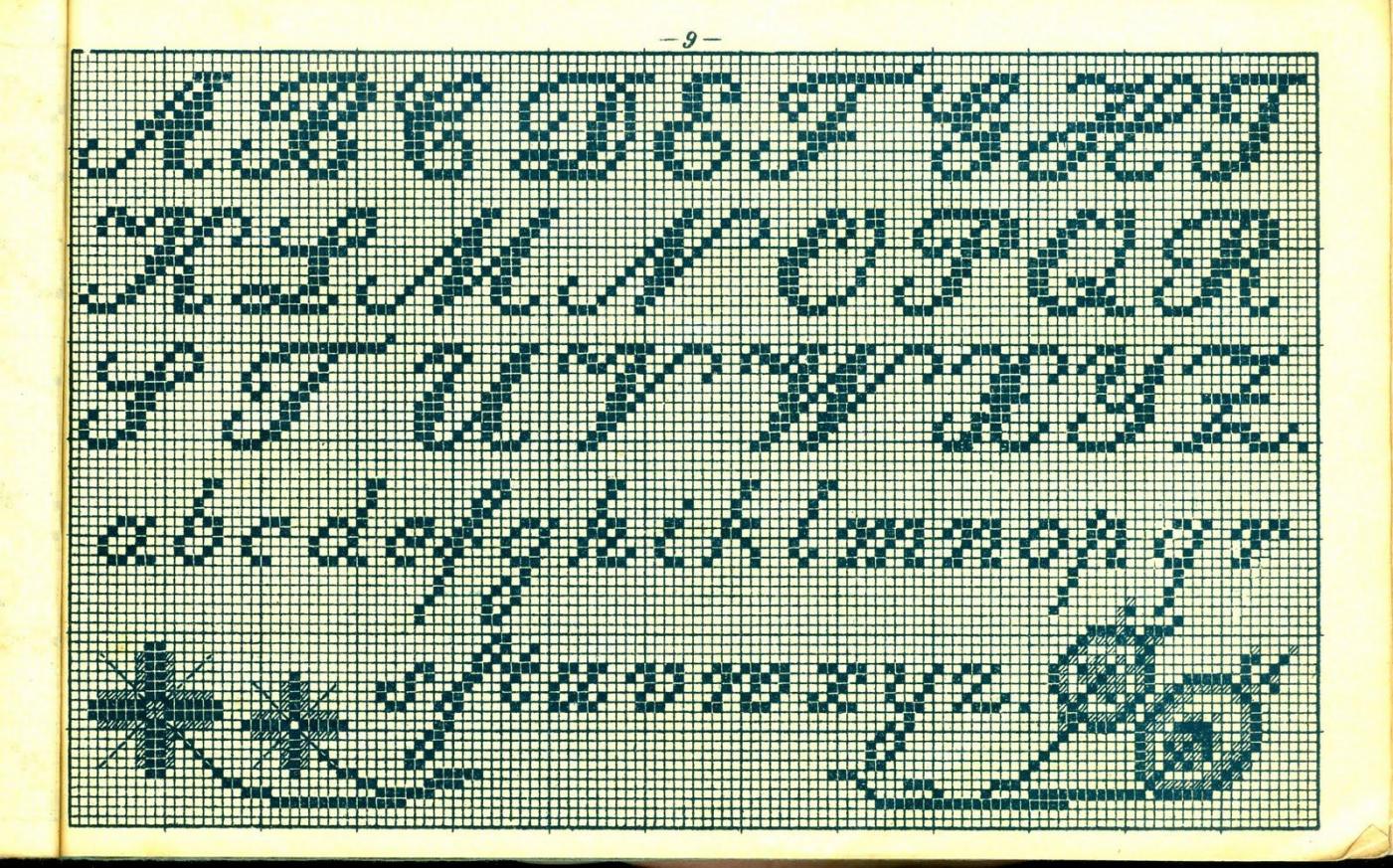
Suche eine lateinische Schreibschrift, bei der das lange s dem kleinen h in der deutschen Kurrentschrift ähnelt
kennt jemand so eine lateinische Schrift, Zu beachten, das das lange s wie das h in einer deutschen Kurrentschrift aussieht.?
die Lithographia von der Bauerschen Gießerei wäre eine Schriftart, die mir gefallen würde.
Gibt es die oder eine ähnliche auch als Computerschrift?
Unter Deinem Link
https://www.myfonts.com/fonts/astype/gracia-series-50/
habe ich noch auf die Schnellen die
https://www.myfonts.com/fonts/3ip/remsen-script/
https://www.myfonts.com/fonts/3ip/botanical-scribe/
https://www.myfonts.com/fonts/3ip/american-scribe/
gefunden.